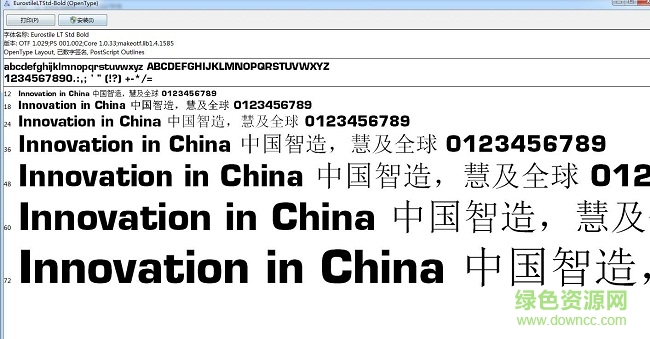
eurostileltstd字體
字體涵義
字體,又稱書體,是技術(shù)制圖中的一般規(guī)定術(shù)語,是指圖中文字、字母、數(shù)字的書寫形式。
eurostileltstd字體
黑體字體特征
黑體漢字抹掉了漢字手書體的一切人為印跡及其造字淵源,沒有手書的起始和收筆;它以幾何學(xué)的方式確立漢字的基本結(jié)構(gòu)(它是構(gòu)建性的,而非書寫性的),其均勻的筆劃寬度和平滑的筆劃弧度表現(xiàn)出一種穩(wěn)定的、充滿機(jī)器意味的無時(shí)間性及共時(shí)性特征。